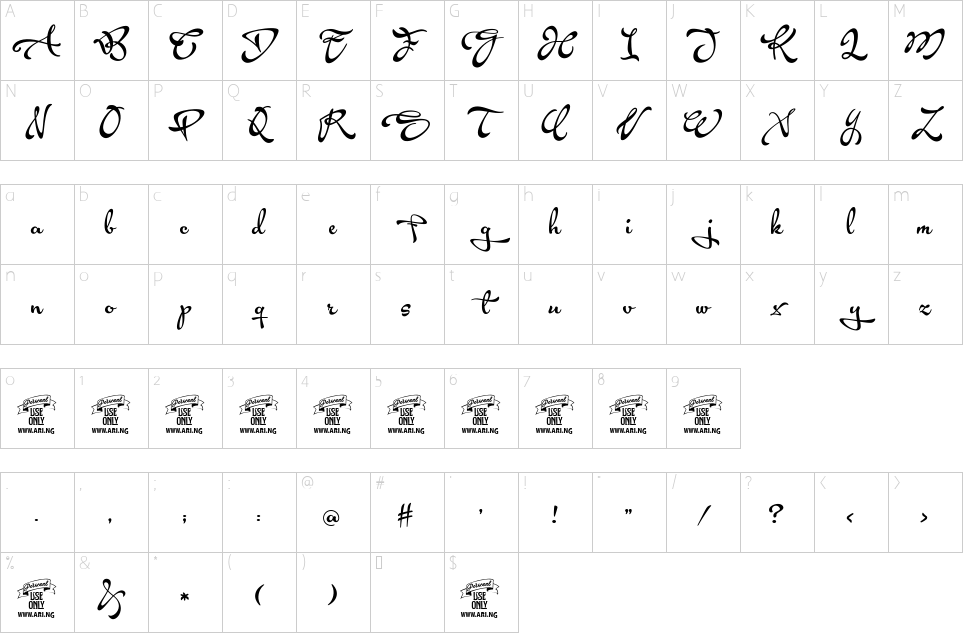
A fonte Acryle Script oferece uma escrita elegante e sofisticada, perfeita para gráficos de alta qualidade. Desenvolvida pelo designer Måns Grebäck, a fonte é conhecida por sua versatilidade e capacidade de criar textos impactantes. Seja para uso em sites, aplicativos ou design gráfico, Acryle Script é uma escolha ótima para quem busca qualidade e criatividade. Com downloads superiores a 225,236 vezes, esta fonte se destaca como uma opção confiável para designers de todos os níveis. Aqui, encontrará uma fonte gratuita, perfeita para aqueles que buscam uma combinação única de elegância e funcionalidade.